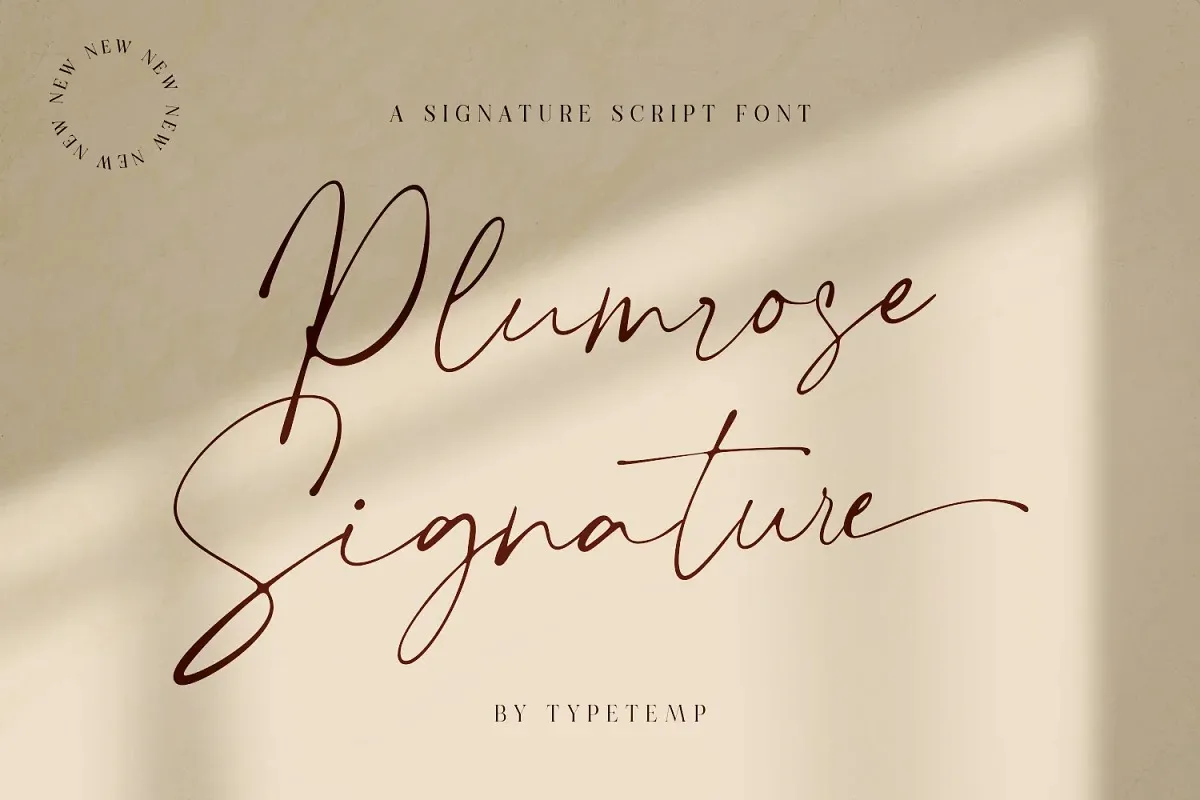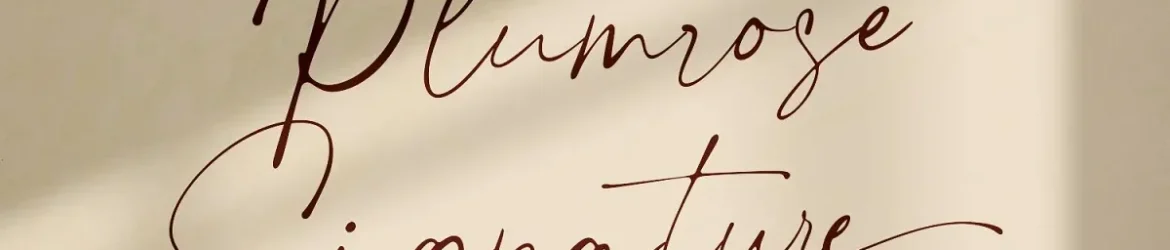
A fonte ‘Plumrose Signature Font’ é uma elegante tipografia script feita para agradar aos olhos, projetada especialmente para uso em diversos projetos digitais e físicos. Feita pelo Designer 99designs, ela oferece um toque autêntico e moderno às suas criações, com alternativas de letras adicionadas que permitem maior flexibilidade no seu design. Suas características de ligaturas e suporte multilíngue a tornam uma fonte versátil. Ideal para editoriais criativos, identidades de marca, eventos como casamentos ou qualquer projeto romântico. Além disso, também é perfeita para uso em designs de produtos, estaçãoários ou anúncios digitais e físicos. A sua sofisticação também permite que a plumose o aplique sobre qualquer imagem de fundo, tornando-a ainda mais interessante. Com ‘Plumrose Signature Font’, você pode adicionar um toque único aos seus projetos, seja para uma viagem romântica ou apenas para dar um toque pessoal e especial ao seu próximo design.